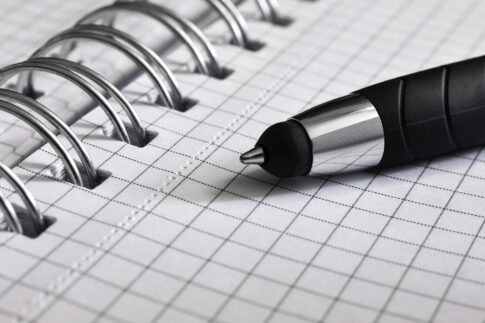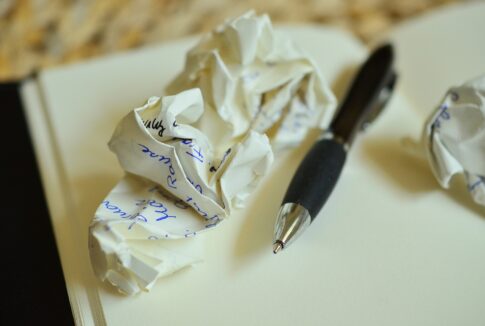
これから字の練習を始めたいけど、ペンにもいろいろ種類あるし、お手本も何を選べばいいのか…とお悩みの方もいると思います。
ということで、今日はペン字の練習に必要な文房具を紹介したいと思います!
まず、必要となるのは以下の4つになります。
①ペン字練習帳or字典(お手本として使います)
②ペン (ボールペン・筆ペンなど)
③硬筆用ソフト下敷きorボール紙
④米字格ノート (なければ50字用の書き取り帳でも可)
それでは、一つ一つ順に見ていきましょう!
①ペン字練習帳or字典
これは、一番重要です。お手本次第で今後目指す字の方向性が決まるといっても過言ではありません。
ここで、お手本を選ぶポイントを3つ挙げていきます。
①「学習指導要領準拠」の教材を使う
絶対に学習指導要領準拠でなければいけないわけではありませんが、
美しい字の定義を確認したい人、字を基本から学びたい人は、「学習指導要領準拠」の教材がおすすめです。
学習指導要領とは、文部科学省が告示しているもので、学校教育法に基づいて決められた教育課程の基準のことです。
学習指導要領は全国のどの地域でも一定の水準の教育を受けられるようにする為のものなので、それに準拠した教材は基礎的な知識や技術がしっかり盛り込まれています。
また、小中学生にも分かりやすいように書かれているので、初心者の方でも取り組みやすくなっています。
ちなみに、私がペン字の練習で使っているのは、二玄社の「常用漢字 書き方字典」というものになります。
ノートとペンを準備して、書きたい文字をこの辞書で調べながら書いていく感じです。
②字が大きく、説明が分かりやすく書かれているもの
書道教材ではよくあるのですが、書家の作品だけが書いてあって、細かい書き方などは一切載っていないものがあります。
現に私もこうした教材は使っているので、決して悪いものではないのですが、初心者の方からすると放任されているように感じる可能性があります。
ですので、綺麗に書くためのポイントを説明してくれている教材を使うことをお勧めします。
③自分好みの字であること
これからお手本と長く付き合っていくのは自分自身なので、「こんな字を書けるようになりたい!」と強く思える字でなければ、継続は難しいでしょう。
①で挙げた「学習指導要領準拠」教材は品質は高いのですが、楽しく学べるというよりは堅実に学んでいきたい方に合っていると思います。
「もう少し気楽な感じで練習していきたいよ。」という方は、ペン字練習帳がおすすめです。
ペン字練習帳は、お手本と練習ノートが一体化されているので、ペンとこれ1冊あればすぐに練習を始められます。
また、ペン字練習帳は日常生活の中でも比較的よく使われるシーン(冠婚葬祭、自分の名前や住所など)に絞って作成されているので、効率よく練習をしていくことができます。
ちなみに私からおすすめできるペン字練習帳はこちらです。
クセのない字形が特徴で、多くの人が好むであろう字形だと個人的には思います。
ひらがな、カタカナから始まり、楷書、行書、日常書式まで対応しており、たくさん練習することができます。
②書きやすいペン(ボールペン・筆ペン)
ペンの書きやすさやインクの色は字の美しさに大きく影響を与えます。
さらっとした書き心地のペンは手首に余計な力が入らないのでおすすめですし、インクの色は黒々と艶がある方が綺麗に見えます。
ちなみに普段、私が使っているボールペンは、こちらです。
人気のあるボールペンなので、皆さんの中にも使っている人は結構いるのではないでしょうか?
個人的には、0.5が細すぎず、太すぎずちょうど良いと思います。
ボールペン字は鉛筆よりも力を入れず、紙の上を滑るように書いていくので、インクの出が悪いものは避けるようにしましょう。
さて、筆ペンでおススメなのは、こちらです。
年賀状や封筒書きの時はこれがおすすめですね。
また、色付きの筆ペンであれば、こちらも書きやすいです。
金色のほかに、銀色もあります。
インクが滑らかで非常に書きやすい筆ペンです。
③硬筆用ソフト下敷きorボール紙
下敷きには大まかに分けて、ハードタイプとソフトタイプがあります。おそらく、皆さんが学生の頃に使っていたのは前者の方が多いのではないでしょうか?
ソフトタイプの良いところはペン先が滑りすぎるのを防止してくれるところです。
ハードタイプの下敷きを使用すると自分が思っている以上にペン先が動いてしまって、思ったような字を書きにくくなります。
ペン先が滑りすぎないようにするには、この下敷きがおすすめです。
また、下敷きではなく、ボール紙を下敷きとして使うのもおすすめです。
ボール紙もペン先を安定させてくれるので書きやすいのです。
ただ、ボール紙を下敷きとして使っていると、筆圧の影響でペンの跡がボール紙に残るので、定期的に変えた方がいいと思います。
④米字格ノートや50字の書き取り帳
字の練習には米字格ノートがおすすめです。
しかし、「米字格って何ぞや(・・?」という方も多いと思います。
(日本ではあまりお馴染みではないと思うので。)
米字格はその名の通り、マス目に「米」字のように補助線が引かれているマスのことです。
ちなみに、このサイトに載せている、ひらがな・カタカナは全てこの米字格ノートに書いたものです。
普通のマスに字を書くよりも、点画の配置が分かりやすくなるので、綺麗な字を書きやすくなります。
米字格ノート以外であれば、50字用の書き取り帳でもOKです。
懐かしいですね。小学校一年生の頃は皆さん使ったのではないでしょうか?
84字や100字を使わない理由としては、字が小さいと自分がどこをうまく書けていないか分かりにくいからです。
たとえば、普段大学ノートに書いている字はそれなりに綺麗なのに、封筒や年賀状に書くとそこまで綺麗に見えなくなってしまう人はいませんか?
その理由としては、自分の字が大きく書かれたことによって、欠点が見えやすくなってしまうからです。
自分が上手く書けていない部分を直視することは勇気がいりますが、できない部分を修正してこそ、字は上手くなります。
巷では、「苦手なところより、自分の得意なところを意識して伸ばそう」と言われていますが、字に関しては「バランス」が大切なのです。
⑤今回の内容のまとめ
さて、今日はペン字の練習に必要な文房具の紹介をさせていただきました。